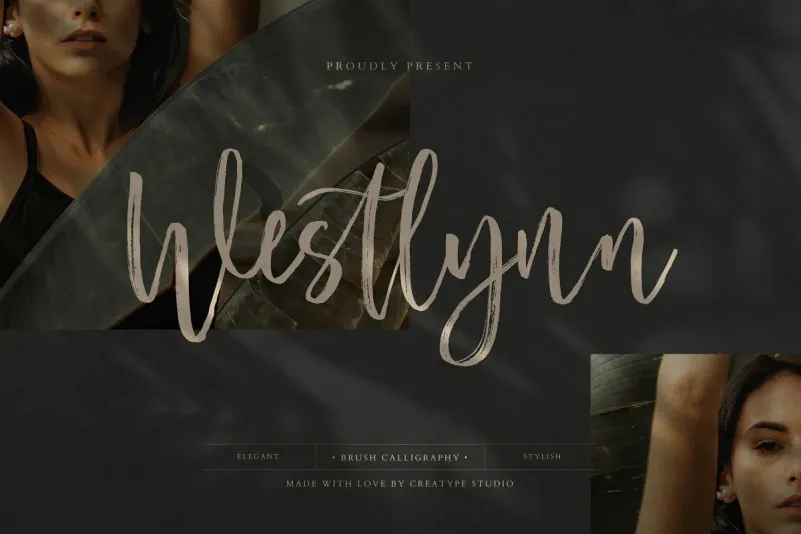
Westlynn Font – Fonte Grátis
Westlynn Font
A Westlynn Font é uma elegante escolha para quem busca um estilo de escrita natural e inspirado na arte manual. Criada com a ajuda de uma ferramenta química, essa fonte possui um toque poderoso devido ao seu design firme e robusto. É perfeitamente adequada para aplicação em diversos projetos visuais. Suas linhas fortes criam um impacto significativo quando usadas em criações como selos de produto, embalagens, cartazes ou até mesmo logotipos. Este tipo font é ideal para qualquer projeto que valorize uma sensação autêntica e quente da escrita manual. Desde etiquetas de produto até anúncios, Westlynn oferece um toque especial em qualquer trabalho visual onde há necessidade de transmitir a essência do texto escrito à mão. Ideal para design de marca, redes sociais, produtos, convites e materiais de embalagem, essa fonte é uma ótima opção para aqueles buscando dar vida aos seus projetos visuais com um toque único e autêntico.